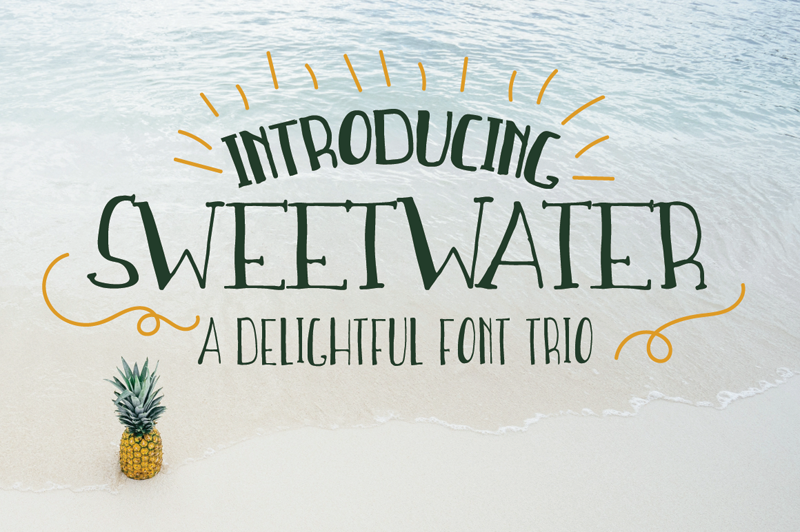
A Sweet Water Font é uma trilogia de linhas elegantes e frescas para quem busca personalidade em seu design. Cada uma das três se destaca em sua própria maneira, oferecendo um sabor único que combina suavidade com força. Essas linhas são perfeitas para aqueles que procuram uma fonte moderna para criar identidades visuais ou projetos de design gráfico. Com suas linhas fluidas e elegantes, o Sweet Water Font não apenas adicionará um toque sofisticado a seus materiais impressos ou digitais, mas também traz à tona uma atmosfera envolvente e natural que certamente chamaria atenção. Para quem deseja experimentar esta trilogia de linhas, basta visitar o site da designer Hamilton: www.milliemaeandco.com. Assim, você pode escolher a fonte perfeita para seu próximo projeto, garantindo uma experiência única e inspiradora.